위메이드 인피니티 산스, 2019 레드닷 어워드에서 본상 수상
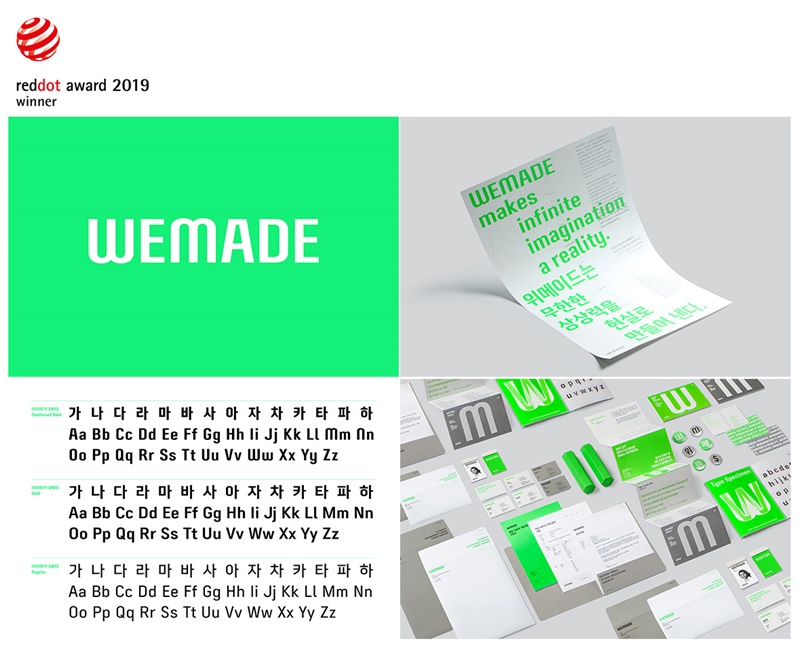
게임회사 위메이드가 ‘2019 레드닷 디자인 어워드’ 브랜드&커뮤니케이션 부문에서 본상을 수상했다. 주목할 점은 심사의 대상이 심볼이 아닌 폰트였다는 점이다.
수상의 배경을 거슬러 올라가면, 위메이드가 올해 폰트회사 윤디자인과 함께 진행한 리브랜딩 작업이 그 시작이다. 기업의 아이덴티티를 재정립하고 기업 전용 서체인 ‘인피니티 산스’를 만들었다. 인피니티 산스는 다양한 요소와 조화를 이루는 황금비율 그리드가 특징으로 ‘무한한 상상력을 현실로 만들어낸다’는 위메이드의 정체성이 집대성 된 서체다.